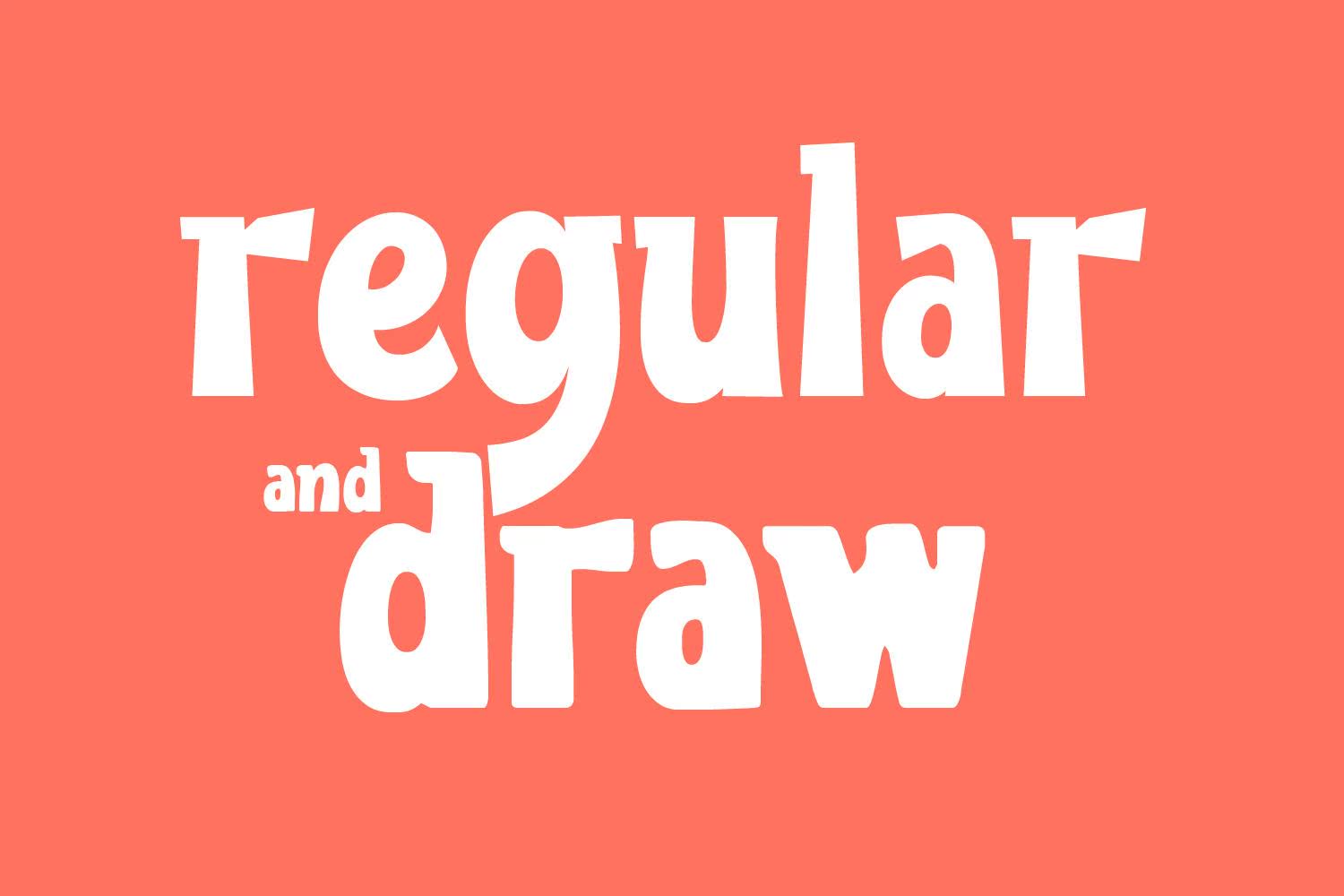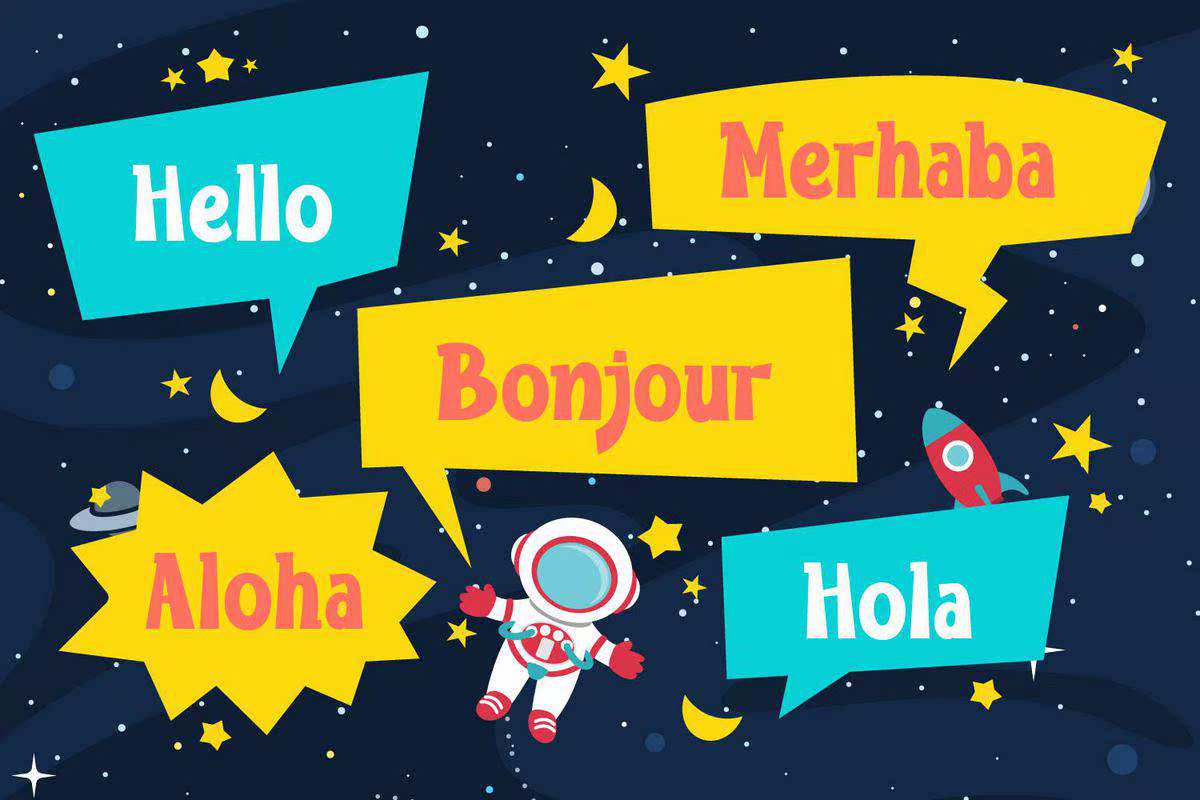
Ldfunbites和Drawn均为纯字体。它们具有规则(干净)和Draw样式。clean样式具有天使角,Draw版本具有良好的手绘效果。Ldfunbits具有可爱的功能特征,适合任何儿童设计,如衬衫、书皮、,Merchandises和许多.ldfunbits还具有多种语言和一些可选字符,您可以在预览中看到。ldfunbits和Drawn采用纯字体。它们具有规则(干净)和Draw样式。CleanStyle具有AngeledAngled和Draw版本,手绘精美。ldfunbits具有可爱和功能特性,适用于任何儿童,如衬衫、书皮、,Merchandisease和manymore.ldFunBits还具有多种语言和一些可在预览中看到的可选字符。